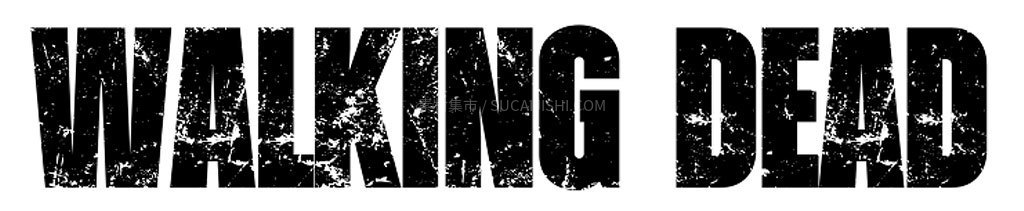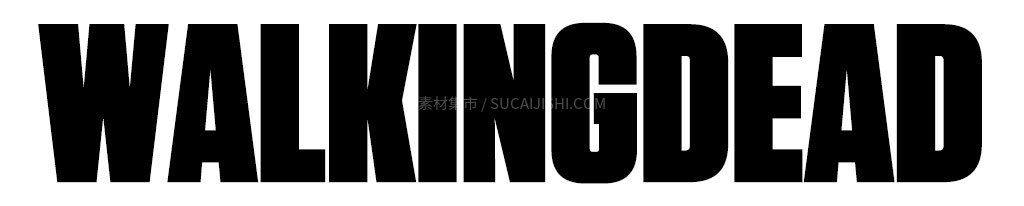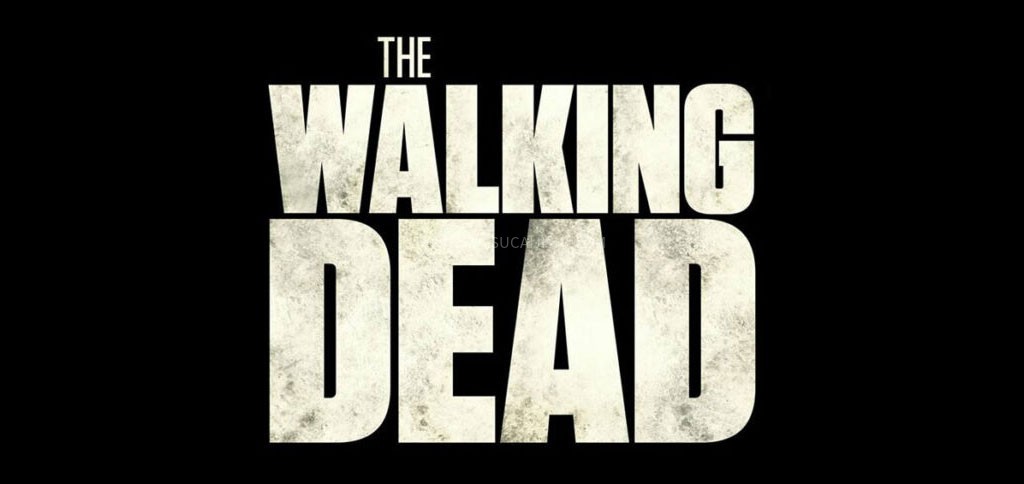
《行尸走肉》The Walking Dead 末日废土风字体
一套复刻自经典末日丧尸题材美剧《行尸走肉》(The Walking Dead)标志的英文字体。包含了三款字体,完美还原了剧集中那种破败、斑驳、充满末世危机与生存挣扎的视觉风格。无论你是该剧的死忠粉,还是需要营造恐怖、废土或惊悚氛围的设计师,这款字体都能为你的作品注入强烈的视觉冲击力。
Tungsten Black (原版)
Wones (平替款)
Dead Kansas (复刻版)